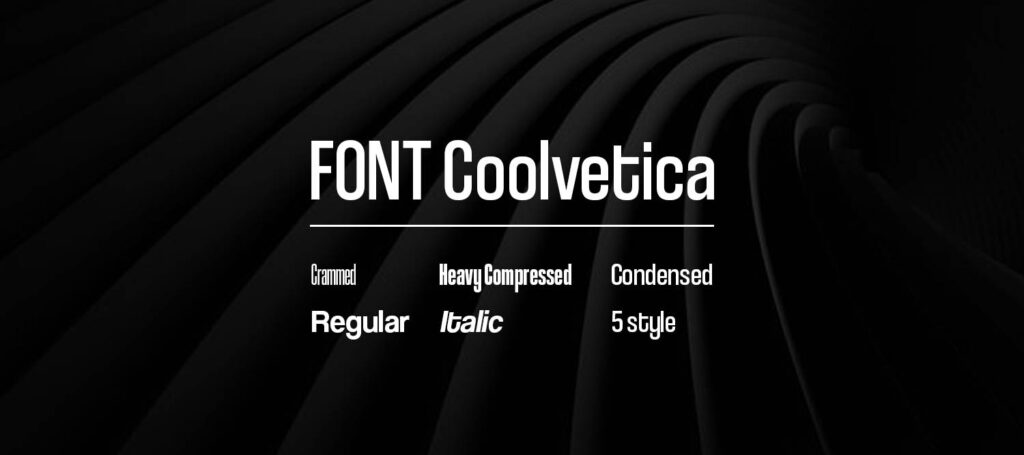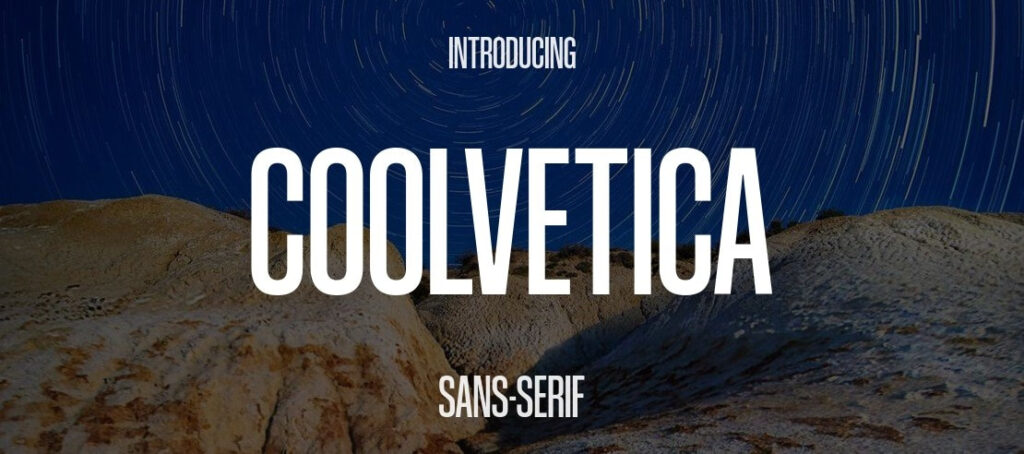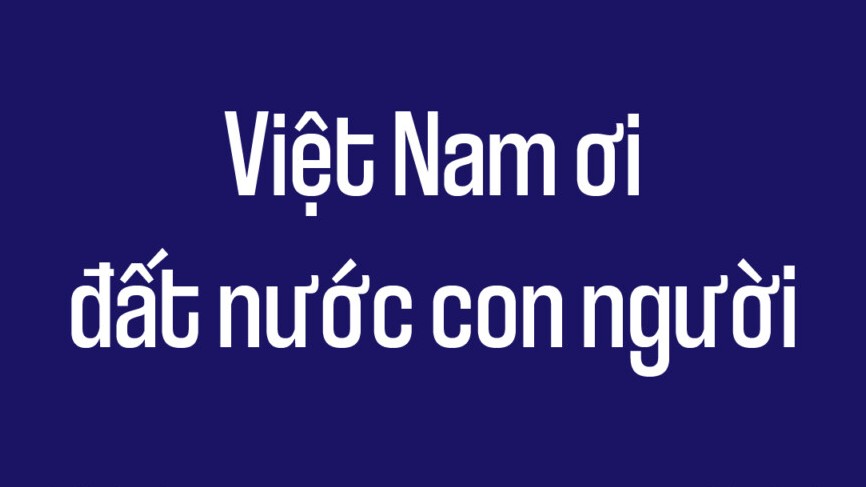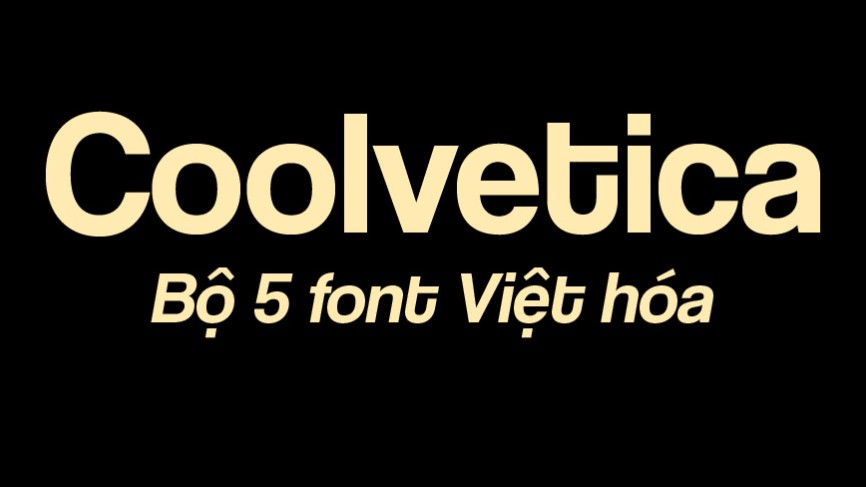
Font Coolvetica là bộ phông chữ thuộc dòng Display Sans-serif nổi tiếng được sáng tạo bởi Ray Larabie, lấy cảm hứng từ phong cách biến tấu đầy nổi loạn của Helvetica trên các logo thương mại thập niên 1970. Với các nét uốn cong tinh nghịch ở đuôi chữ ‘t’ hay ‘y’, kết hợp cùng khoảng cách ký tự cực kỳ sát sao, font Coolvetica Việt hóa là chất liệu trực quan tuyệt vời để các kiến trúc sư, nhà thiết kế thổi bùng cá tính cho các bản vẽ phối cảnh quán cà phê container, ki-ốt bán hàng di động hay biển hiệu homestay dành cho giới trẻ.
Nét uốn cong ngẫu hứng và khoảng cách ký tự đặc thù của font Coolvetica
Điểm cuốn hút của font Coolvetica nằm ở sự kết hợp tài tình giữa bộ khung hình học chuẩn mực và các chi tiết bẻ góc tinh nghịch, mang lại cảm giác sống động và tràn đầy năng lượng. Khoảng cách giữa các chữ cái được thiết kế co cụm có chủ đích, tạo nên các khối chữ liền mạch, đậm tính thị giác và gợi liên tưởng đến những biển hiệu quảng cáo rực rỡ của thời kỳ nhạc Disco.
Sự ổn định về mặt cảm xúc của dòng font này giúp xóa nhòa vẻ ngoài nghiêm nghị của các khối nhà xây dựng công nghiệp. Khi xuất hiện trên các bề mặt vật liệu hiện đại như vách tôn sóng container sơn màu tươi sáng, tấm alu bóng bẩy hay các hộp đèn LED định hình, Coolvetica tạo nên điểm nhấn kiến trúc độc đáo, thu hút ánh nhìn từ khoảng cách xa.
03 Ứng dụng phông chữ Coolvetica vào công trình thực tế
Nhờ vẻ ngoài phá cách và tính gợi hình mạnh mẽ, bộ phông chữ này mang lại giá trị thực tế lớn trong khâu tạo điểm nhấn cho các công trình hiện đại:
- Biển hiệu mặt tiền cho Quán Trà sữa và Ki-ốt Container: Những nét chữ co cụm đậm nét của Coolvetica rất ăn ý khi gia công chữ nổi bằng mica màu cam hoặc vàng tươi gắn đèn LED sáng chân, mang lại diện mạo rực rỡ và thu hút giới trẻ ghé thăm check-in.
- Hệ thống nhận diện cho Khu vui chơi và Tổ hợp sáng tạo: Phông chữ này khi in trên các tấm tôn đục lỗ hoặc dán decal kính sẽ giúp không gian sinh hoạt chung của nhà lắp ghép toát lên chất năng động, khơi gợi cảm hứng khám phá.
- Bìa hồ sơ ý tưởng kiến trúc phong cách Pop Art: Sử dụng font Coolvetica regular cho tiêu đề tập hồ sơ giúp ấn phẩm toát lên vẻ ngoài tươi mới, thể hiện sự nhạy bén của đơn vị thiết kế đối với các xu hướng thẩm mỹ thịnh hành.
03 Lưu ý bố cục font Coolvetica regular Việt hóa duy trì tính sắc nét
Để khai thác hiệu quả vẻ đẹp của dòng font đậm chất đồ họa này mà không gây cảm giác ngột ngạt cho bản vẽ, người thiết kế nên lưu tâm một số kinh nghiệm sau:
- Chủ động nới rộng khoảng cách chữ khi cần: Mặc dù nét đặc trưng của Coolvetica là khoảng cách chữ rất sát nhau, nhưng khi ứng dụng cho các biển hiệu ngoài trời quan sát từ cự ly xa, bạn nên nới rộng nhẹ khoảng cách giữa các chữ cái để tránh hiện tượng dính nét.
- Tránh sử dụng cho văn bản dài: Cấu trúc chữ co cụm và các nét uốn đuôi của Coolvetica không phù hợp cho các đoạn văn bản thuyết minh chi tiết. Hãy giới hạn trong các cụm từ ngắn từ 2 đến 4 từ để tạo điểm nhấn thị giác tập trung.
- Lựa chọn gam màu tương phản cao: Coolvetica phát huy hiệu quả thị giác tốt khi phối cùng các tông màu rực rỡ như vàng nghệ, cam đất, xanh cổ vịt hoặc đen than trên nền trắng tinh khôi, làm nổi bật đường nét uốn lượn của bộ chữ.
2. Tại sao các chữ cái trong font Coolvetica lại đứng sát nhau như vậy?
Đây là chủ ý thiết kế nguyên bản của tác giả Ray Larabie nhằm tái hiện phong cách đồ họa logo những năm 1970. Bạn hoàn toàn có thể dùng công cụ Tracking trong phần mềm đồ họa để kéo giãn khoảng cách chữ theo ý thích.